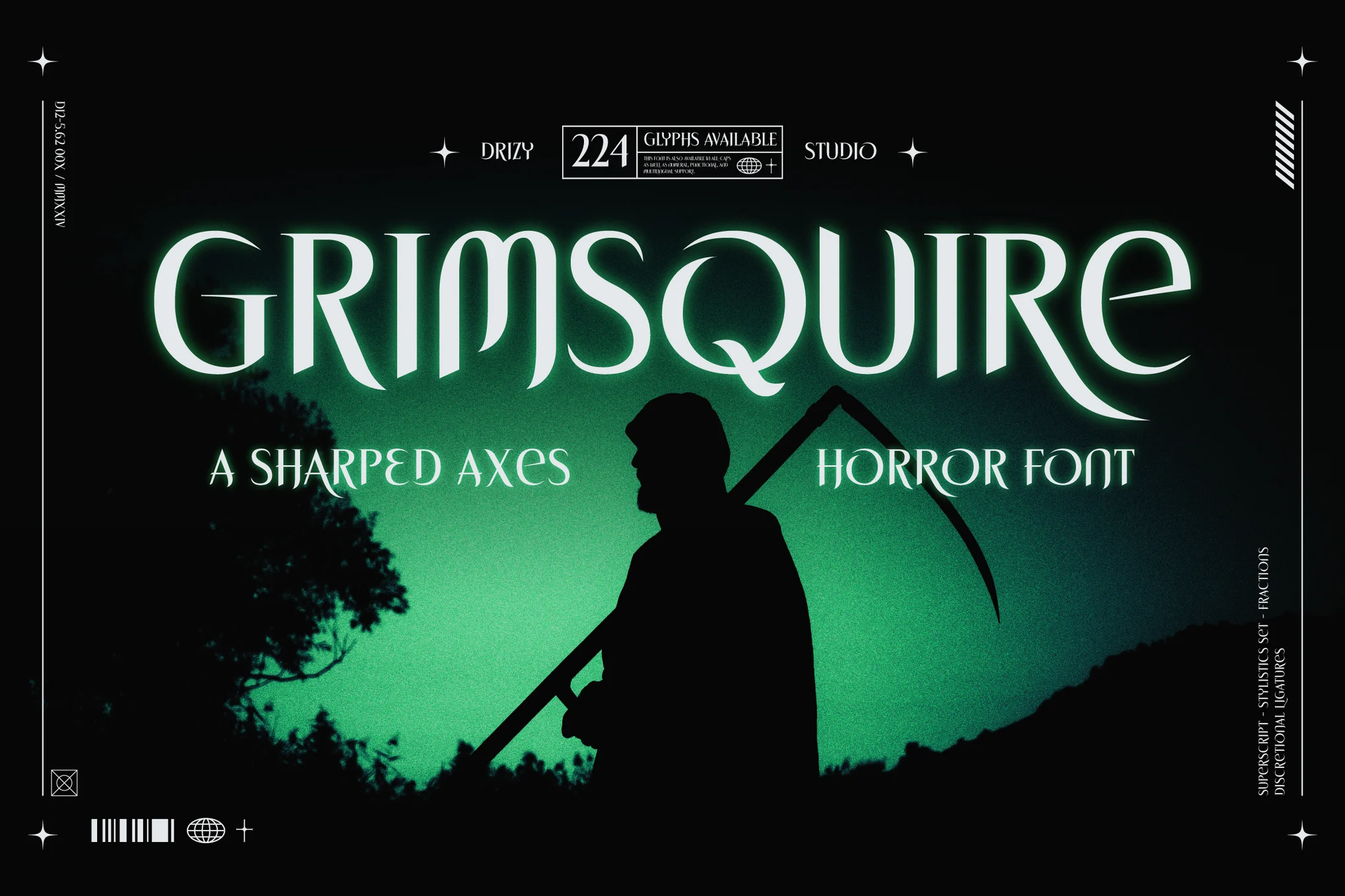
دانلود فونت Grimsquire – Sharped Axes Horror Font
Grimsquire اضافهشدهای دلخراش به مجموعه هالووین ما است، جایی که هر تبر حکایتی از وحشت دارد. این تبرهای تیز شده، که تاریخ تاریک و انرژی بدخواهانه می چکد، فقط ابزار نیستند، بلکه نمادهای ترس و قدرت هستند. هر قطعه در این مجموعه با دقت ساخته شده است تا حس ترس را برانگیزد، که برای کسانی که جرات دارند روح وحشتناک هالووین را در آغوش بگیرند عالی است. چه در حال تزئین یک خانه جن زده باشید و چه به مجموعه با مضمون ترسناک خود اضافه کنید، Grimsquire از کارهای معمولی عبور می کند و تاریک ترین خلاقیت شما را آزاد می کند.